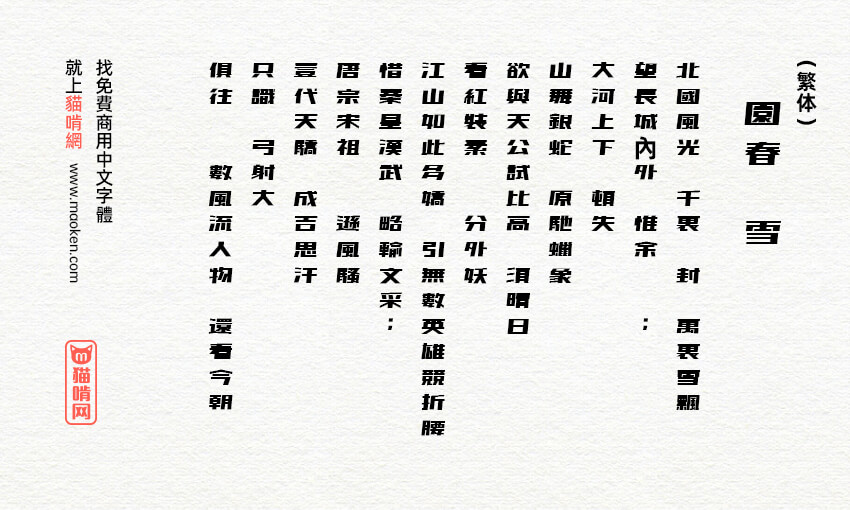
851电机文字体:感受锐利刚劲的力量
字体名称:851电机文字体(851ゴチカクット)PS中字体名称:851ゴチカクット
这是一款充满锐利感的刚性字体,跟我们国内的站酷高端黑的风格相类似,但是它有一定倾斜角度,看上去更有速度感。竖画倾斜5°,目前收录平假名、片假名、数字、JIS第1水准汉字+人名用汉字等。虽然文字还不够多,但是现在作者还有继续开发中,期待能像851手写杂 书 体那样,支持更多的中文字体。